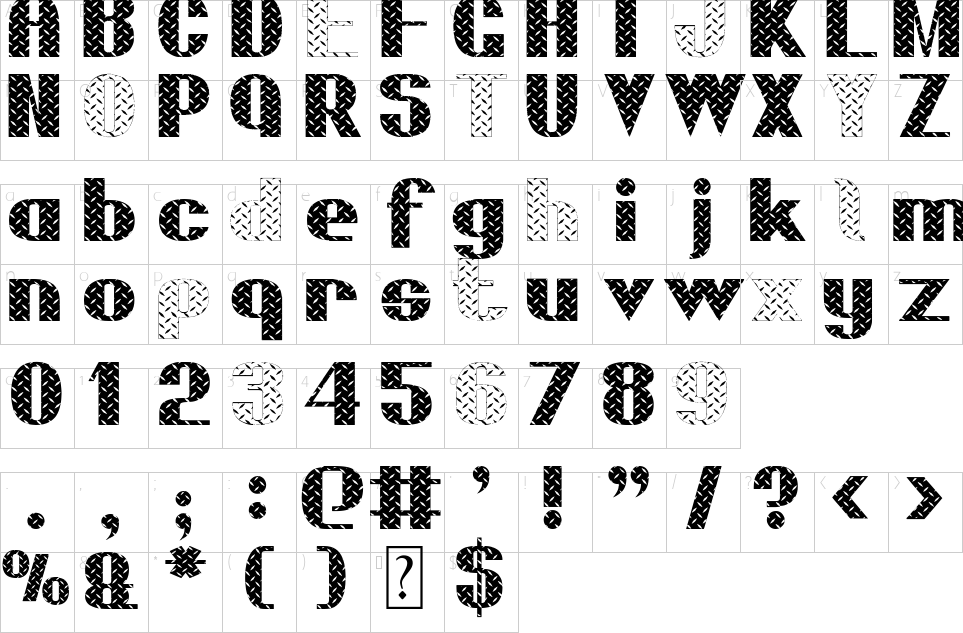
All Diamond Plated Font – Download Grátis
A fonte ‘All Diamond Plated’ é uma escolha inspiradora para designers que valorizam elegância e sofisticação. Desenvolvida por Andrea Steffen, esta fonte tem sido baixada 28,909 vezes, evidenciando seu desempenho notável. Com um design fluido e refinado, ‘All Diamond Plated’ oferece um toque de luxo a qualquer projeto, seja em design gráfico, escrita de marca ou até mesmo em elementos digitais de jogos. Seu design rico em detalhes e seu acabamento perfeito em brilho refletem a elegância de um diamante, tornando-a perfeita para uso em qualquer projeto que busque transmitir uma mensagem de luxo e sofisticação. A fonte está disponível para download em ambas as plataformas Windows e Mac, garantindo que ela seja acessível para designers de todo o mundo.